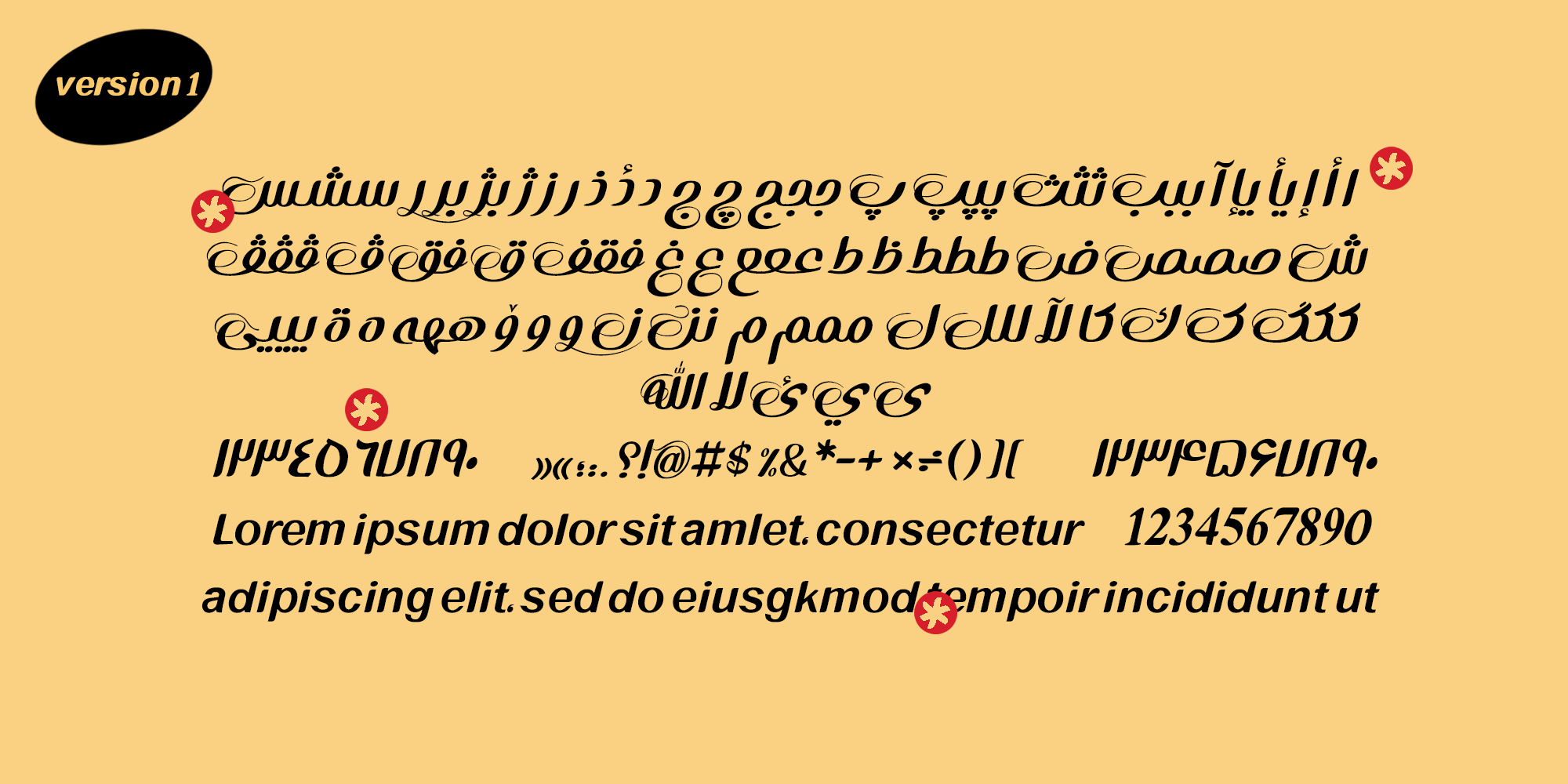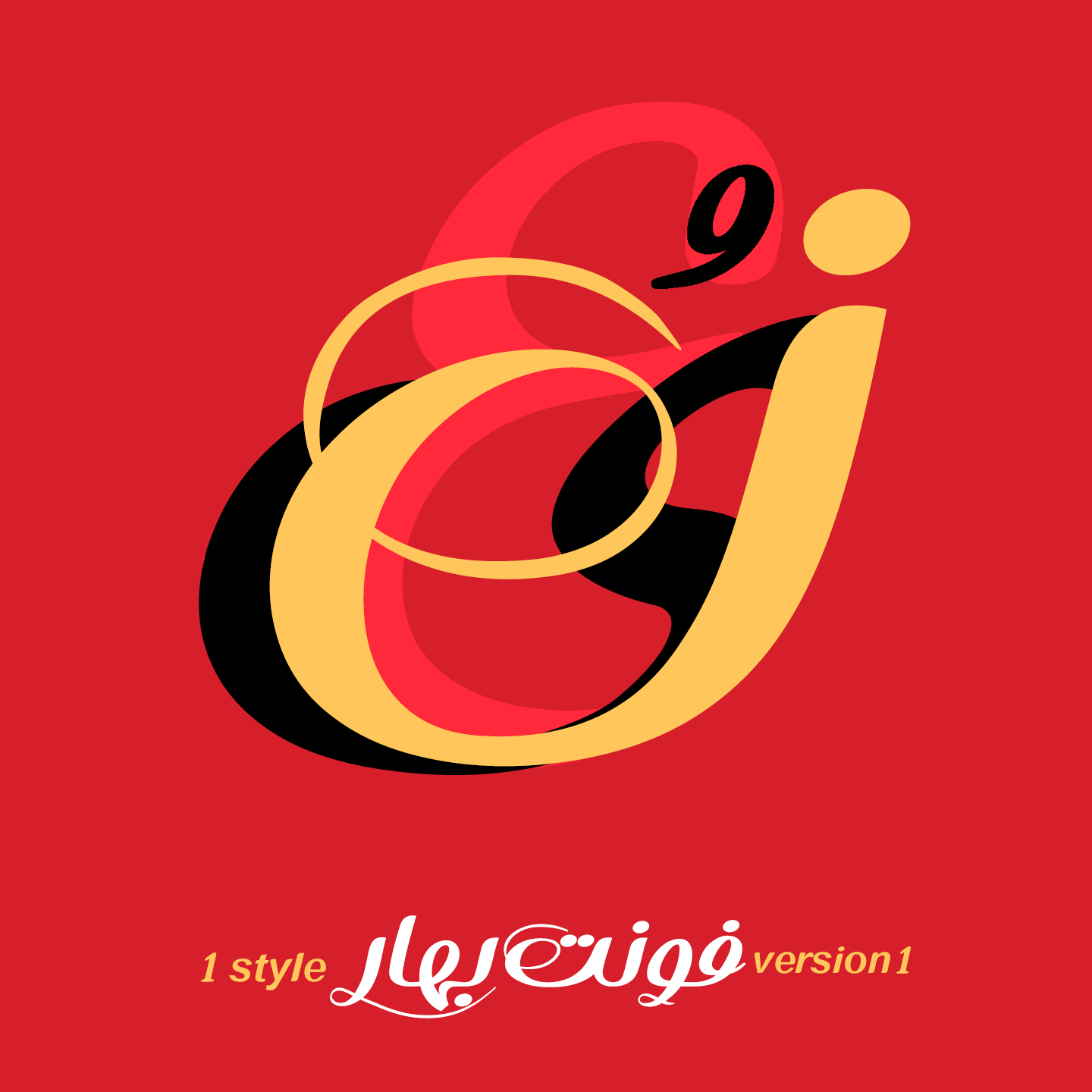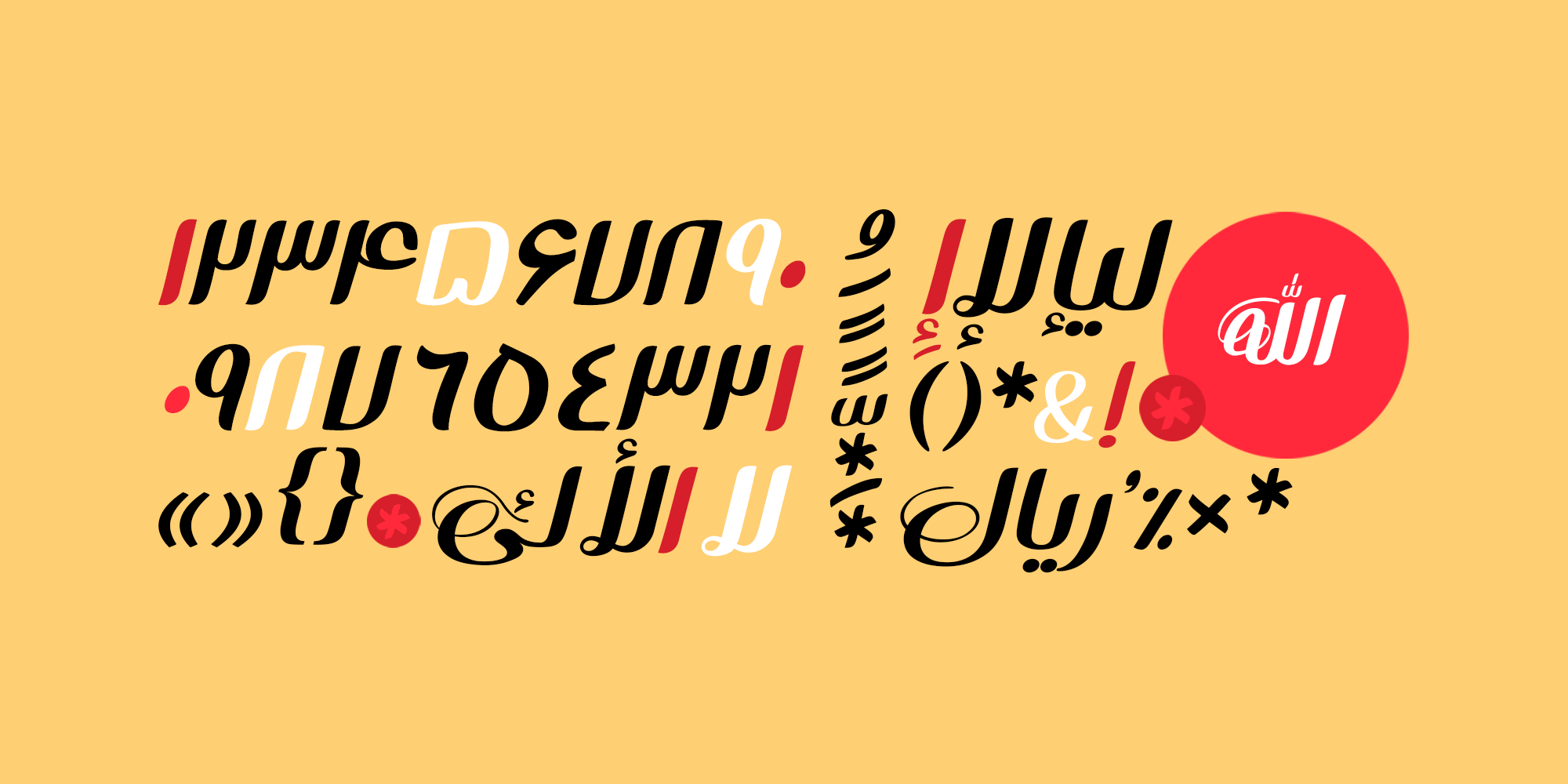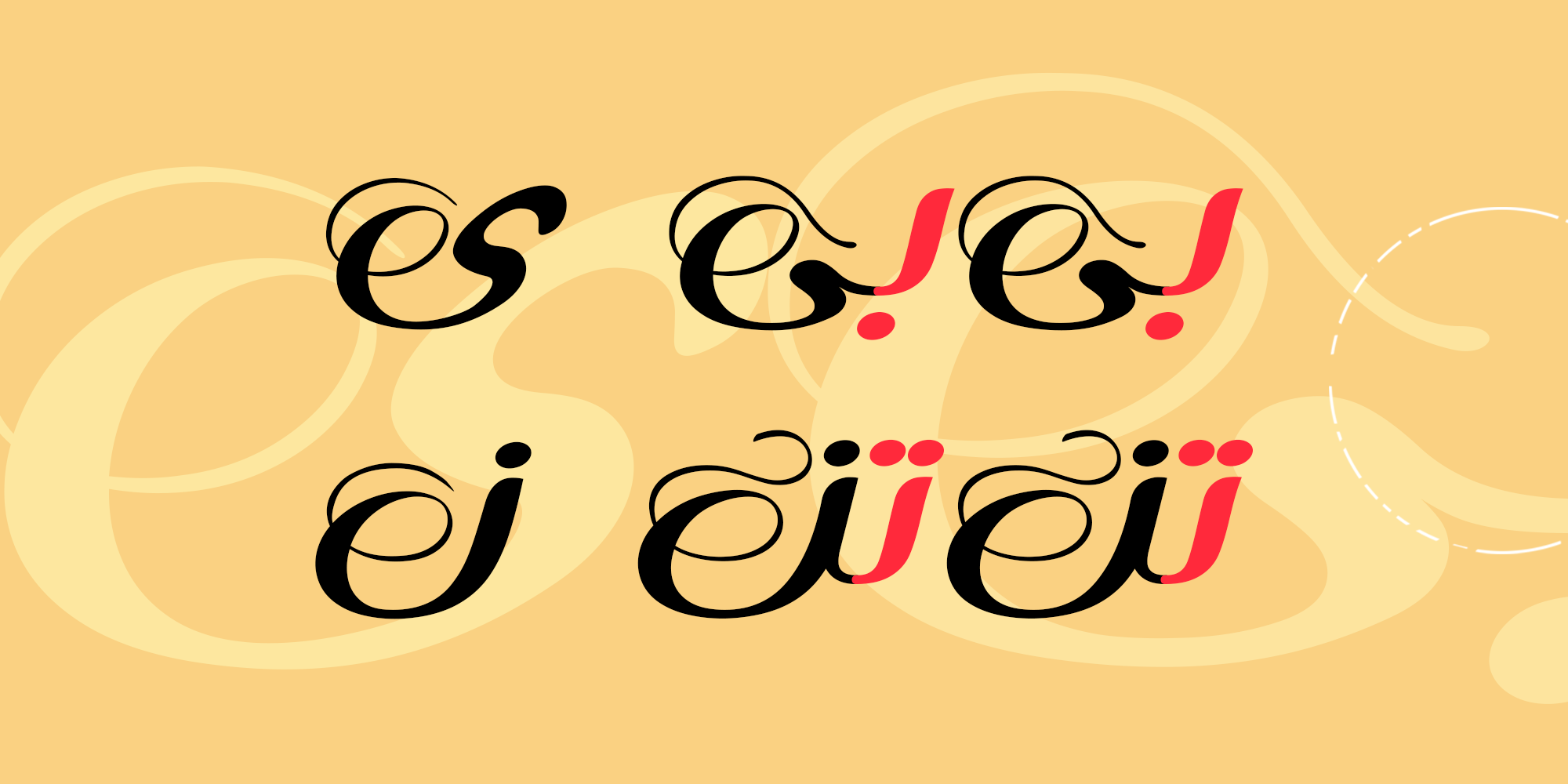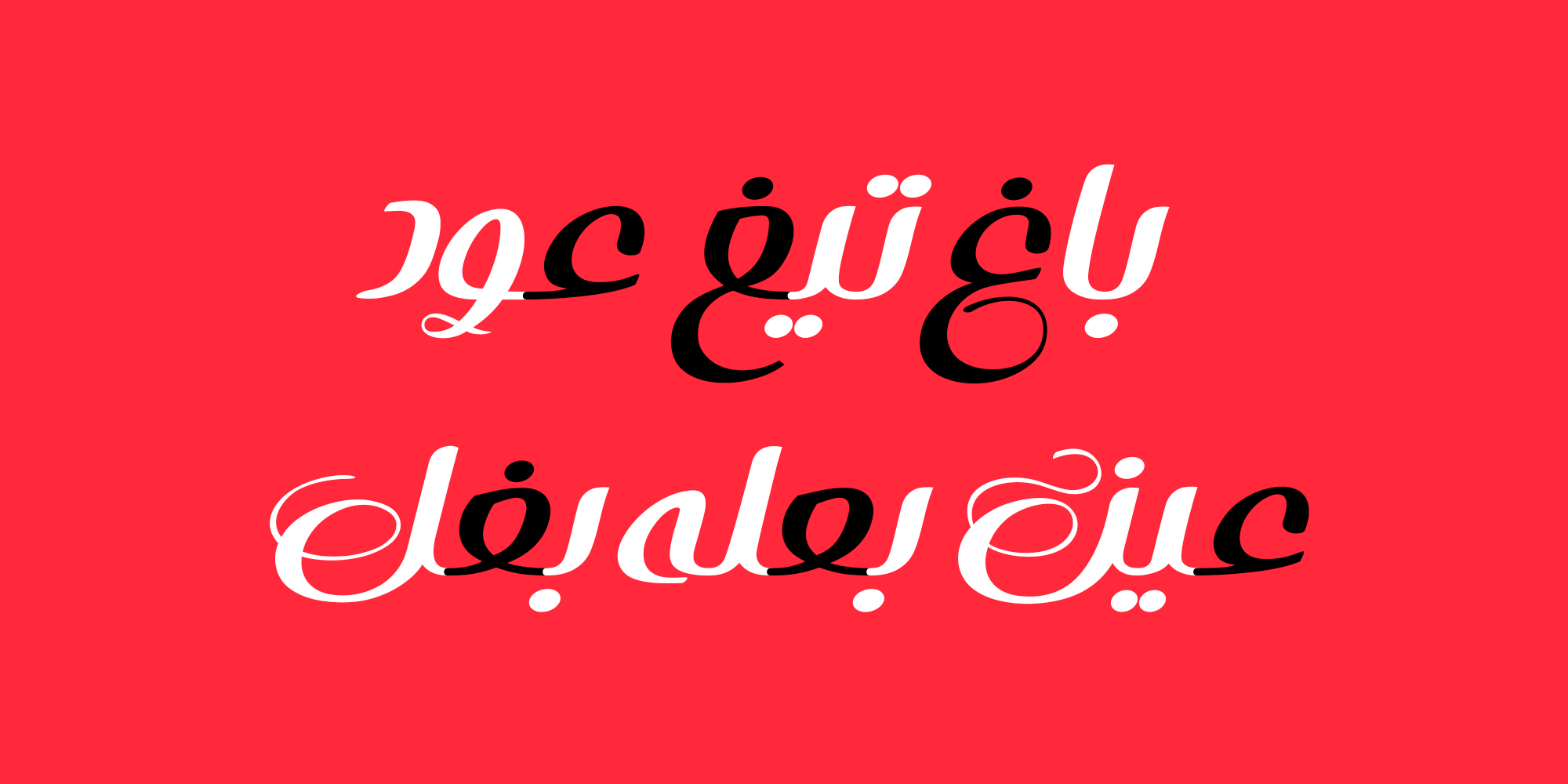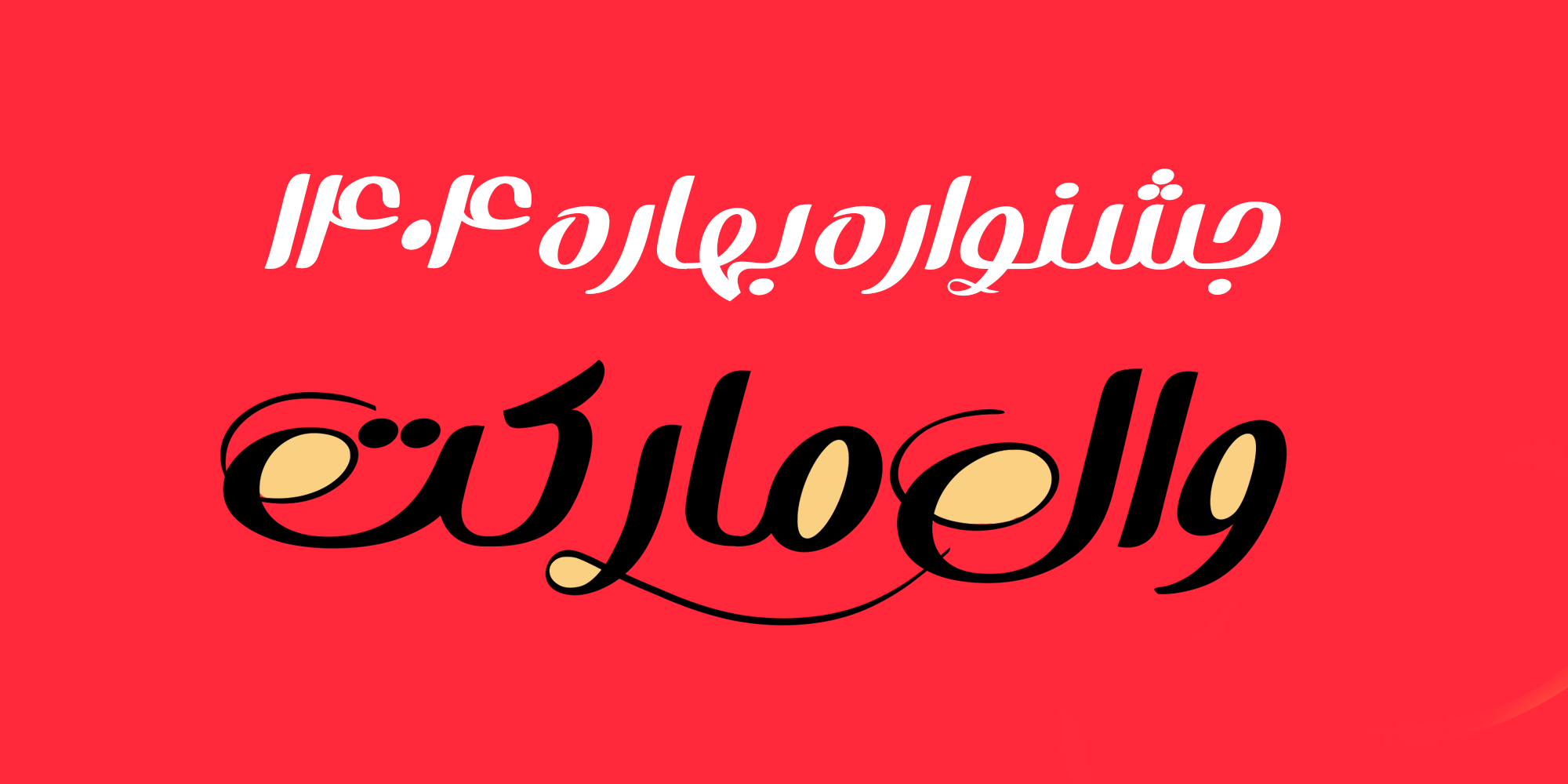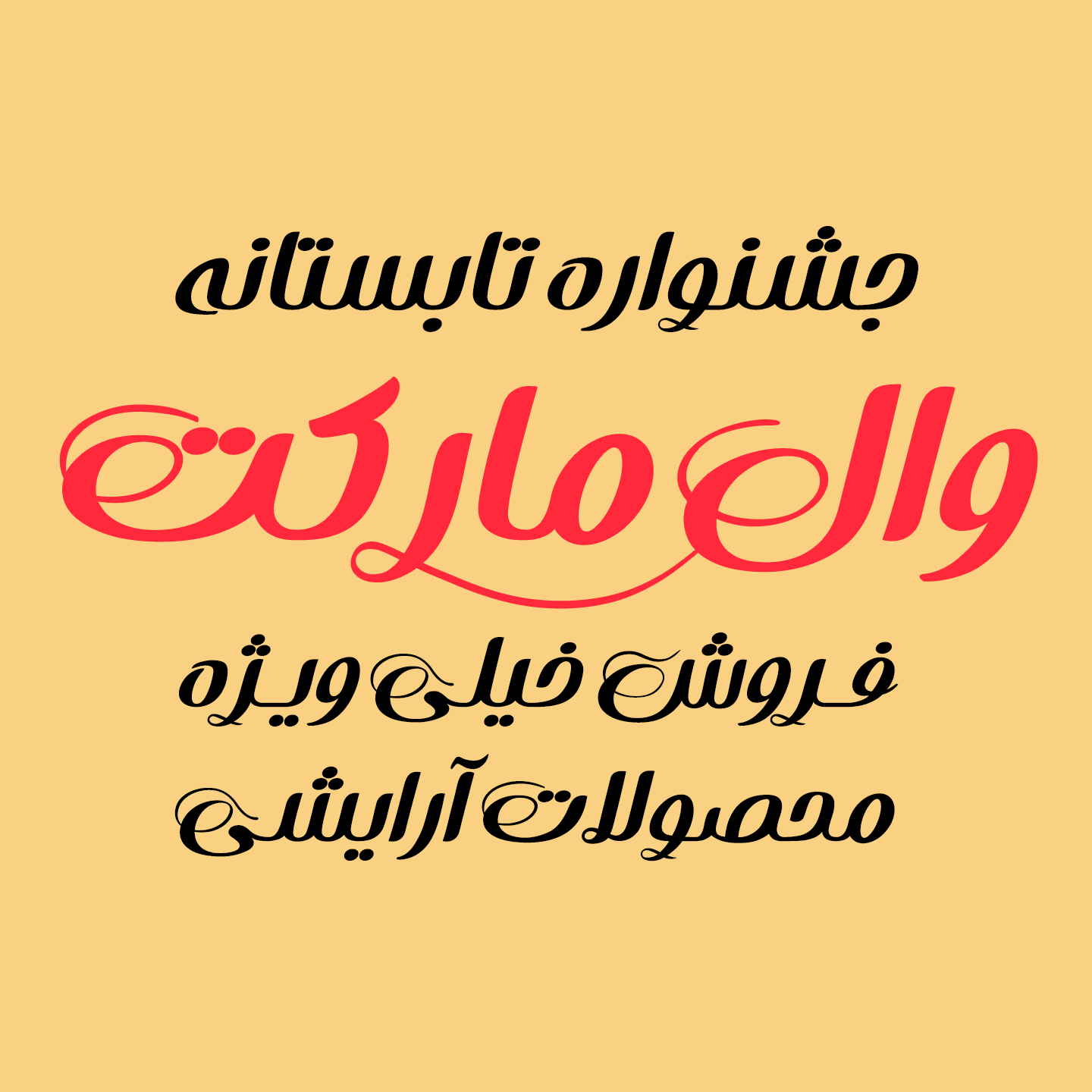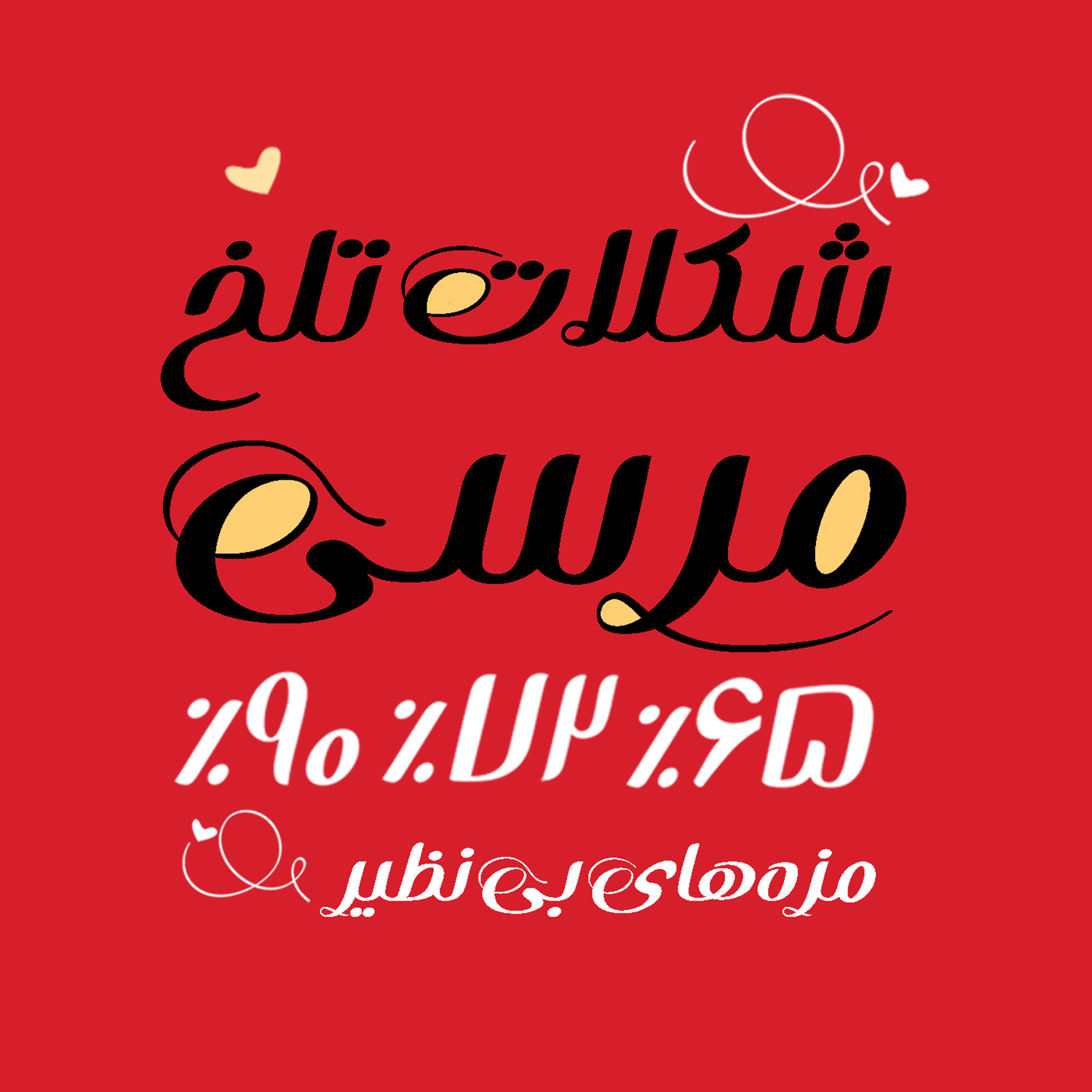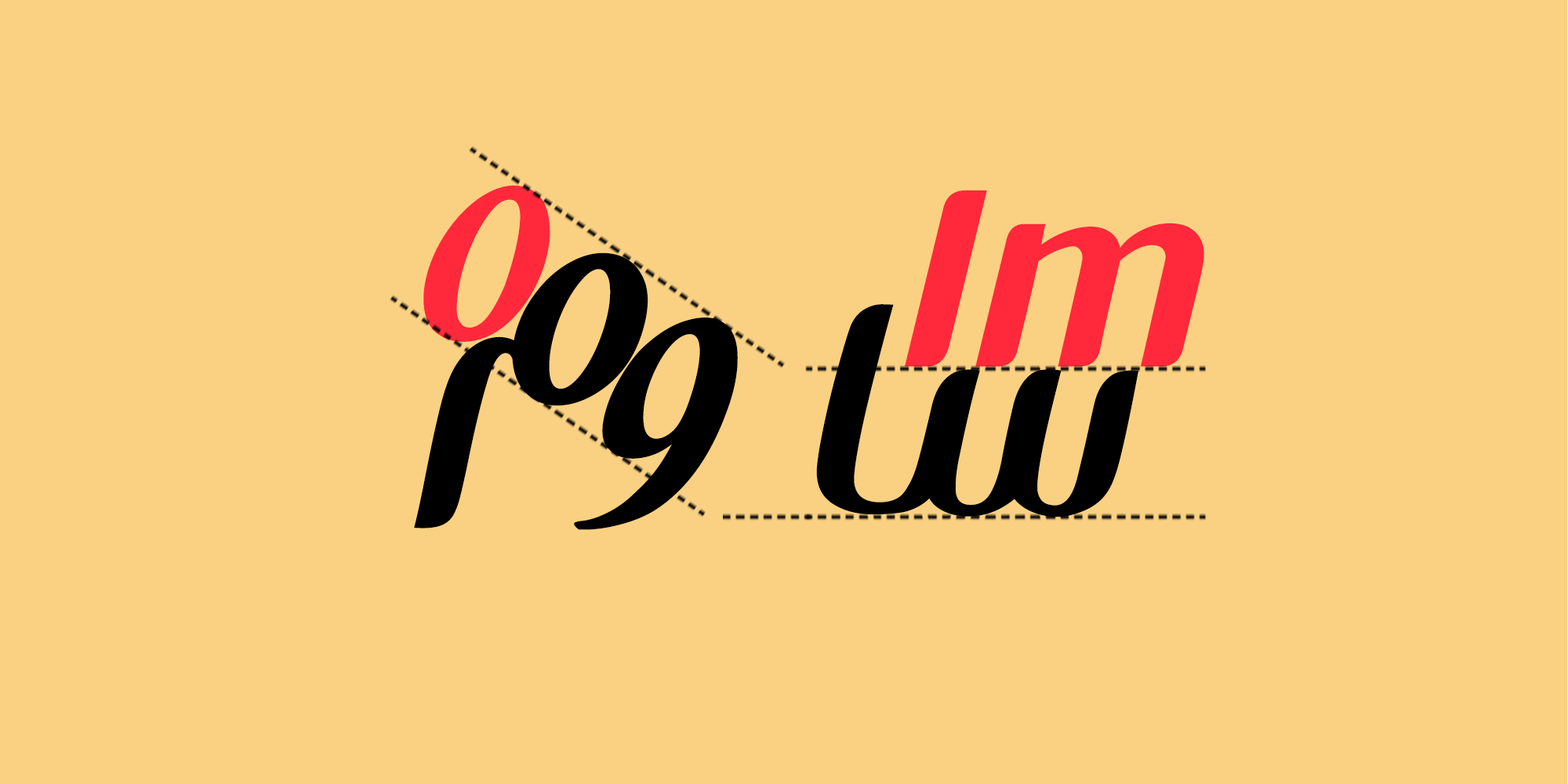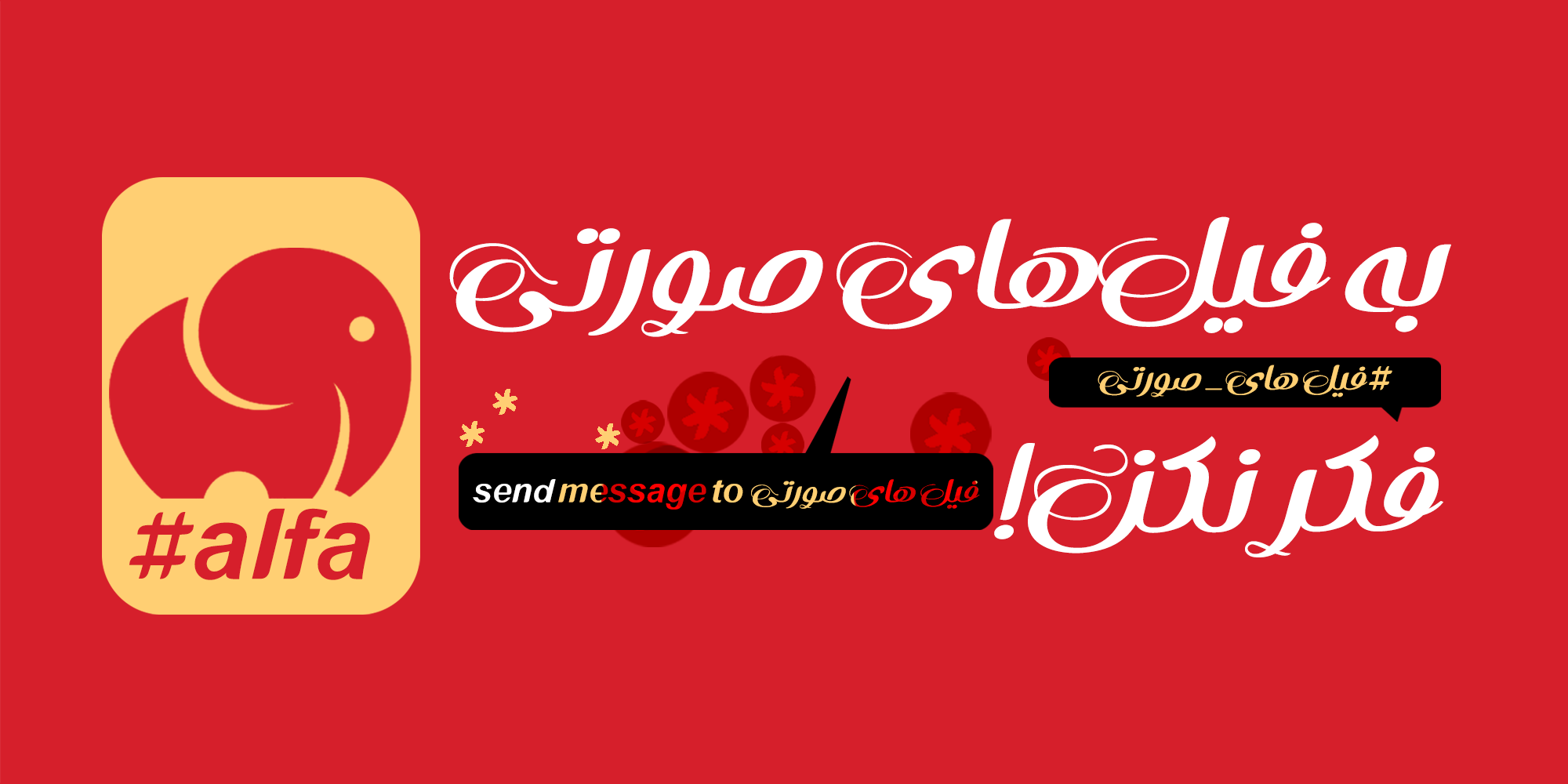
حروف در قسمت خط کرسی زمینه، نازک شده و هنگام فاصله گرفتن از خط زمینه به تدریج ضخیم میشوند. این روند برخلاف حرکات صعودی و نزولی در حالت نسخ است و به همین دلیل حالت لاتینایز به فونت داده و ساختار حروف را منطبق بر سبکهای مدرن میکند به شکلی که برخی حروف شبیه به حروف لاتین دیده میشوند.
فونت بهار نه تنها یک ابزار نوشتاری بلکه یک اثر هنری در قالب کالیگرافی مدرن است که هم به دیزاینرها و هم به آرتیستها پیشنهاد میشود.
ساختار کلی حروف فرم لمیده (ایتالیک) دارند. قوت و ضعف حروف چشمگیر است وچگونگی شروع قلم به کاراکتر کلی فونت حالتی خوشنویسیگونه اما نه به صورت زاویه قلم مورب بلکه با زاویه قلم افقي داده است.
میتوانید حروف «ر» و «و» را در حالت های متصل و منفصل به دو شکل ساده و کرشمه دار استفاده کنید. فعالسازی این ویژگی ساده است و در راهنمای فونت توضیح داده شده است.
برخي حروف به منظور همنشینی بهتر و اصلاح فواصل به صورت ترکیبهای لیگاچری طراحی شدهاند که در تصویر زیر نمونهای از آنها را مشاهده میکنید.
این فونت از حروف و اعداد فارسی، عربی و کوردی پشتیبانی میکند
فونت بهار در تبلیغات